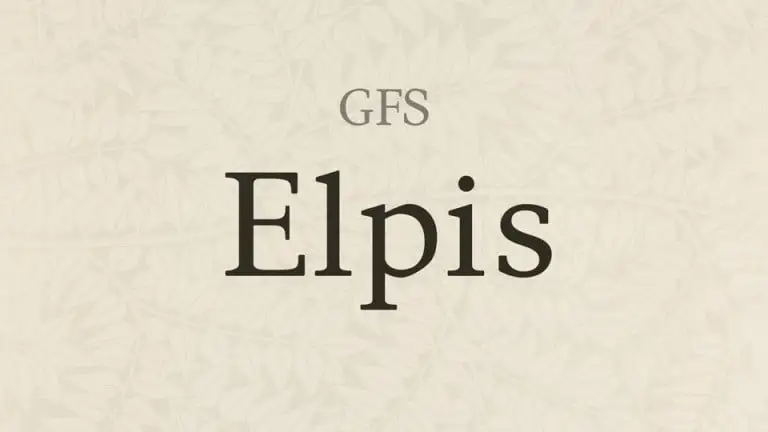
A GFS Elpis Serif Font é uma tipografia serifada robusta com uma design aparentemente muito apertado e limpo, adequando-se perfeitamente mesmo para papéis de baixa qualidade ou impressões de resolução reduzida. Com ascensores curtos e descensores curtos que aumentam a proporção do canto, farpas arredondadas e fortes, e um eixo humanoista, Elpis incorpora ritmo e suavidade com uma ligeira antítese entre as linhas grossas e finas. Esta fonte acompanha também um conjunto de números não ligados e apoia os recursos do tipo aberto como ligações, letras maiúsculas menores, figuras antigas, unidades tabelares e formas sensíveis ao caso. Com seu design atraente e sua diversidade de caracteres, a GFS Elpis Serif Font é uma opção ideal para designers que buscam criar ambientes legíveis e elegantes em qualquer tipo de impressão. Sua versatilidade e capacidade de funcionar em diversos tipos de papel tornam-na uma fonte confiável para aqueles que desejam garantir a qualidade do texto, independentemente da qualidade ou resolução da impressão.